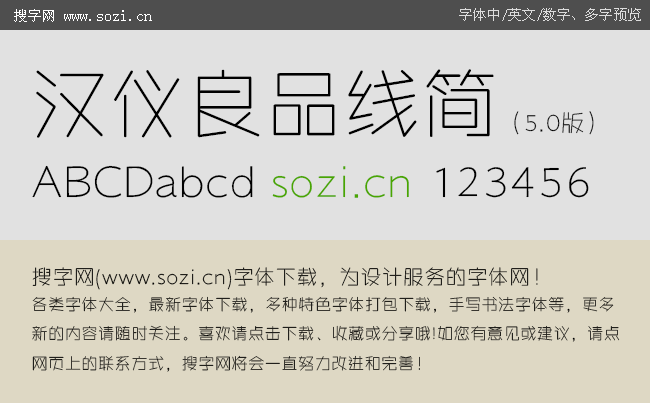
漢儀良品線簡
搜字網(wǎng)提供一款漢儀良品線簡體藝術(shù)字體下載。這款字體清新規(guī)整,充滿簡約的設(shè)計感,重心偏低穩(wěn)定性高,筆畫由直線組成,線條簡單靈動,使人感覺優(yōu)雅有品質(zhì)。在圓體的基礎(chǔ)上加入大膽的改變調(diào)整,使得整套字更有現(xiàn)代感。適合畫冊標題、海報設(shè)計、廣告宣傳等場合使用。
- 風(fēng)格類別: 線體